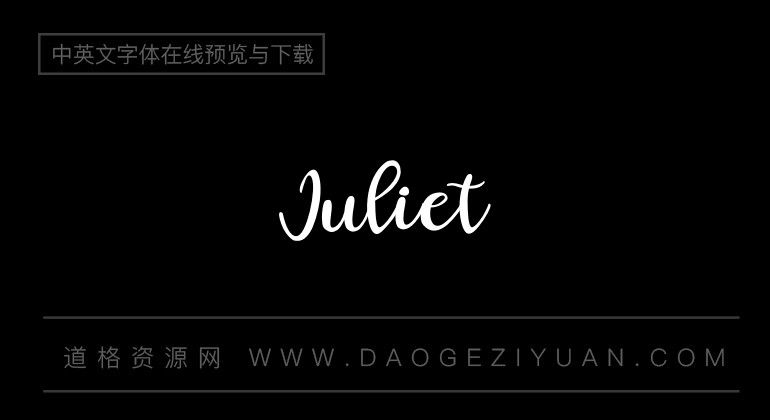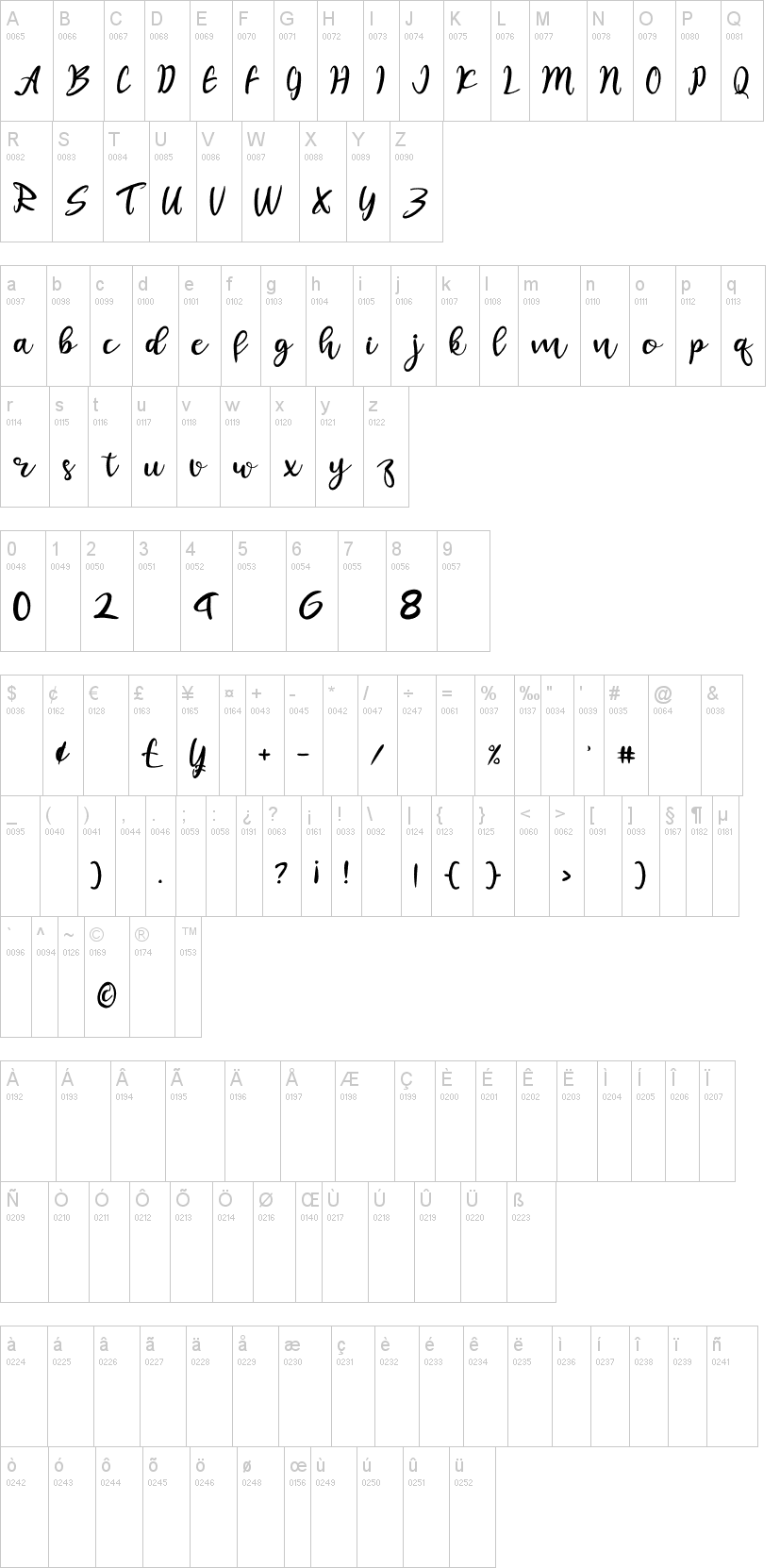
Juliet
? Juliet 字体是一款专为网页设计师和博客写作者而设计的英文字体,它具有流行、现代、优雅的风格,可以让文字更加突出,更容易被读者接受。它有较宽的字母间距,使文章更加清晰易读,同时也有较大的字号,使文章更加突出。Juliet 字体的设计简洁大方,可以让文字更加优雅,更具有吸引力。
Juliet是一款非常不错的手写艺术字体,具有很好的视觉感,适合于文化类的宣传设计、商业类品牌的广告和产品包装设计以及个性化文字排版等较多场景。
Juliet字符映射图